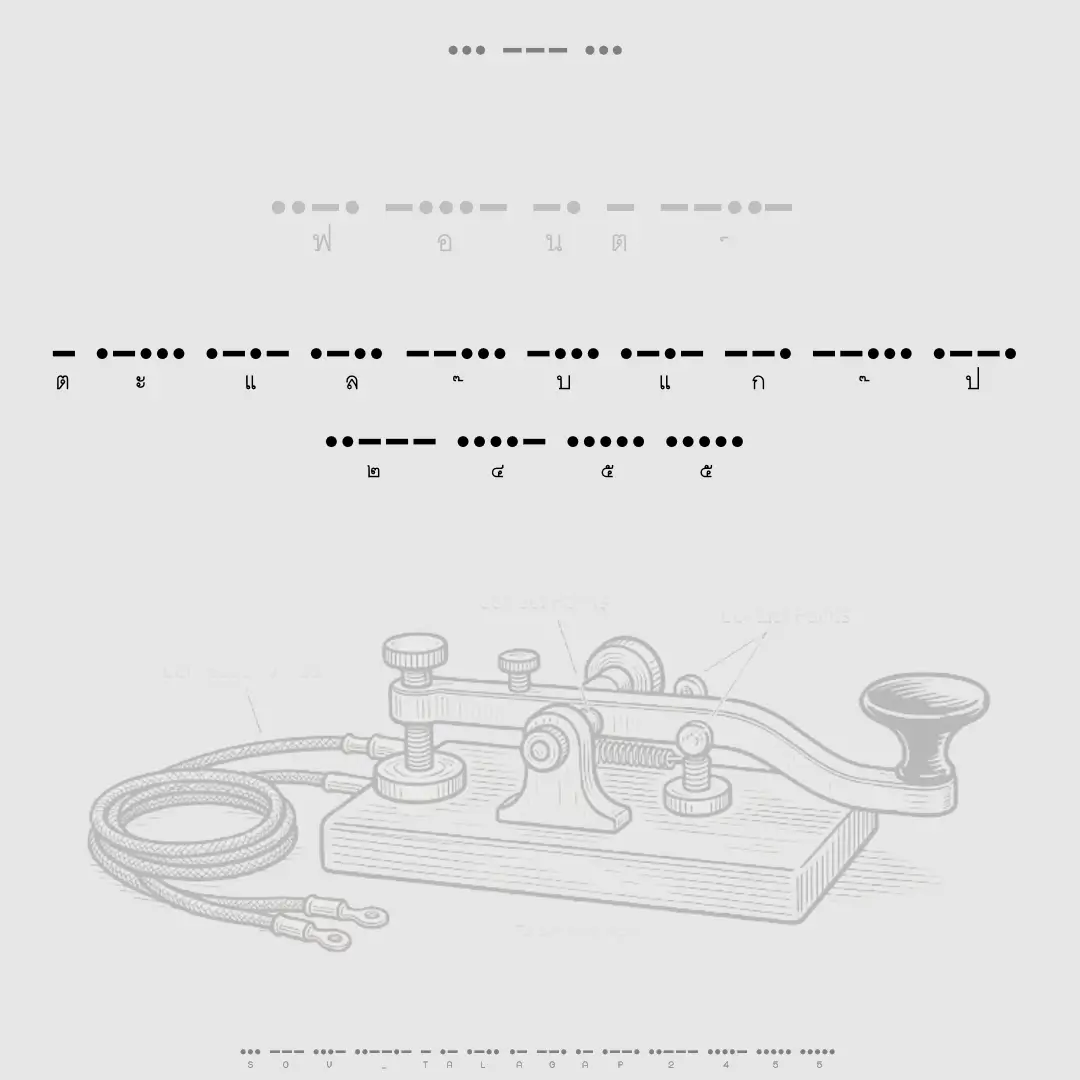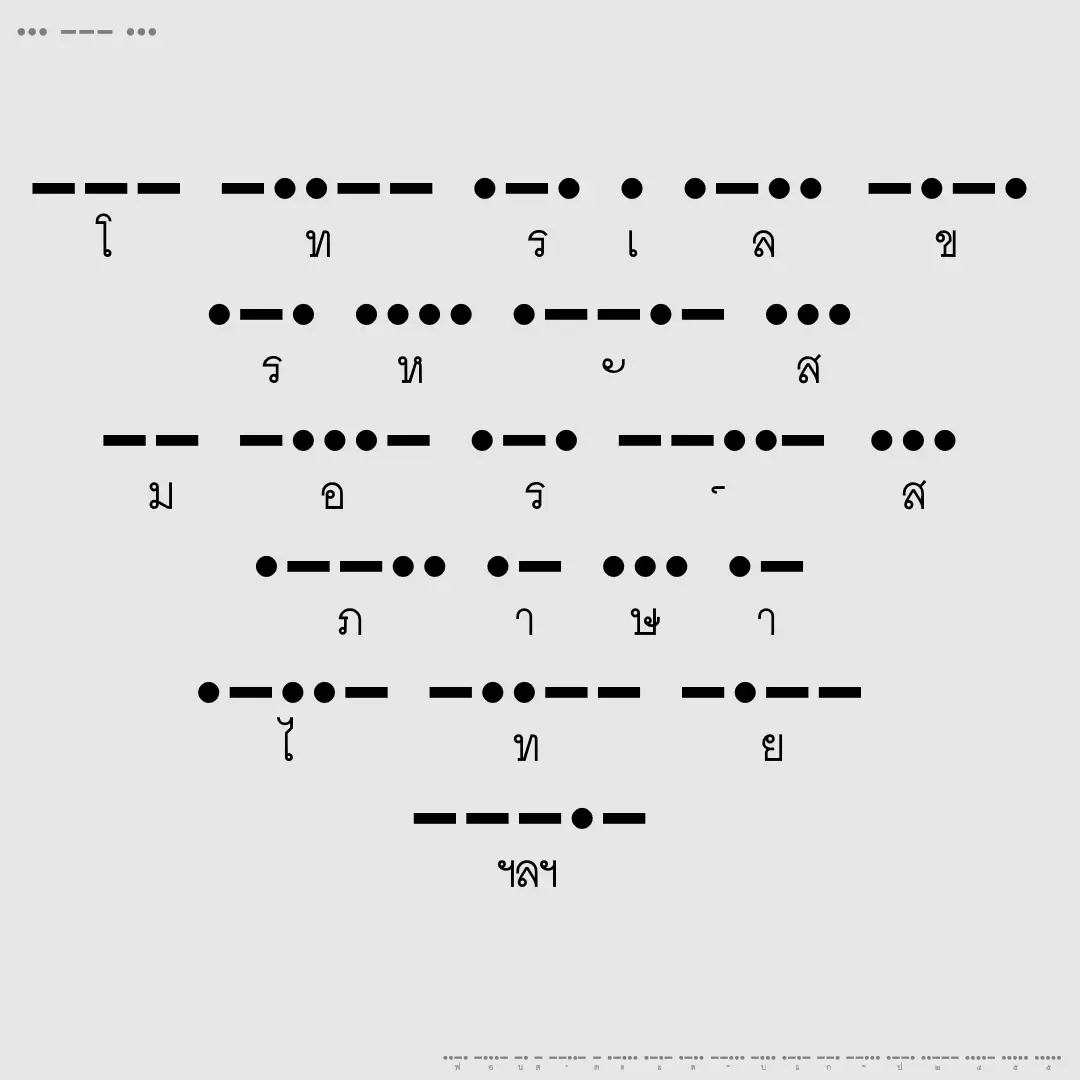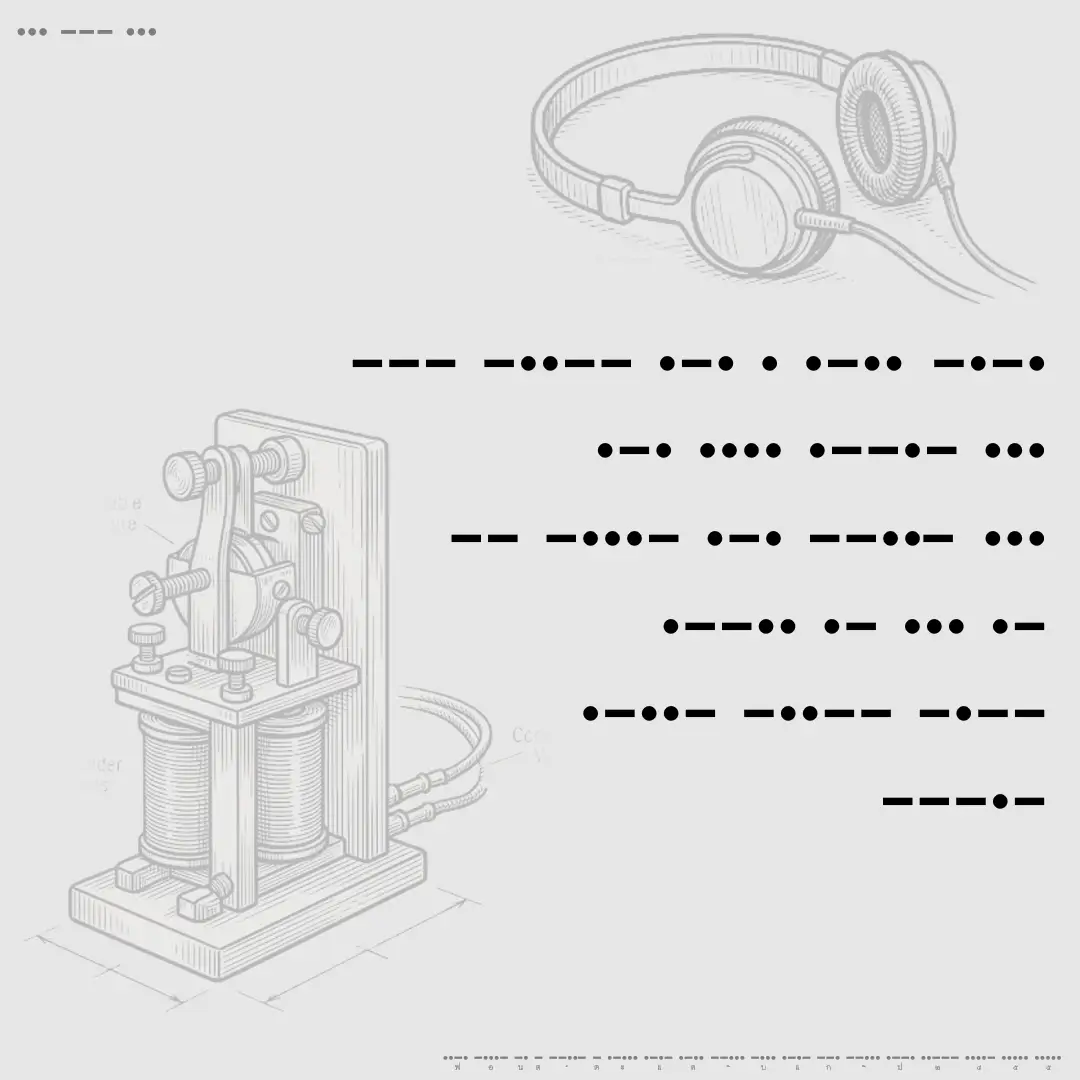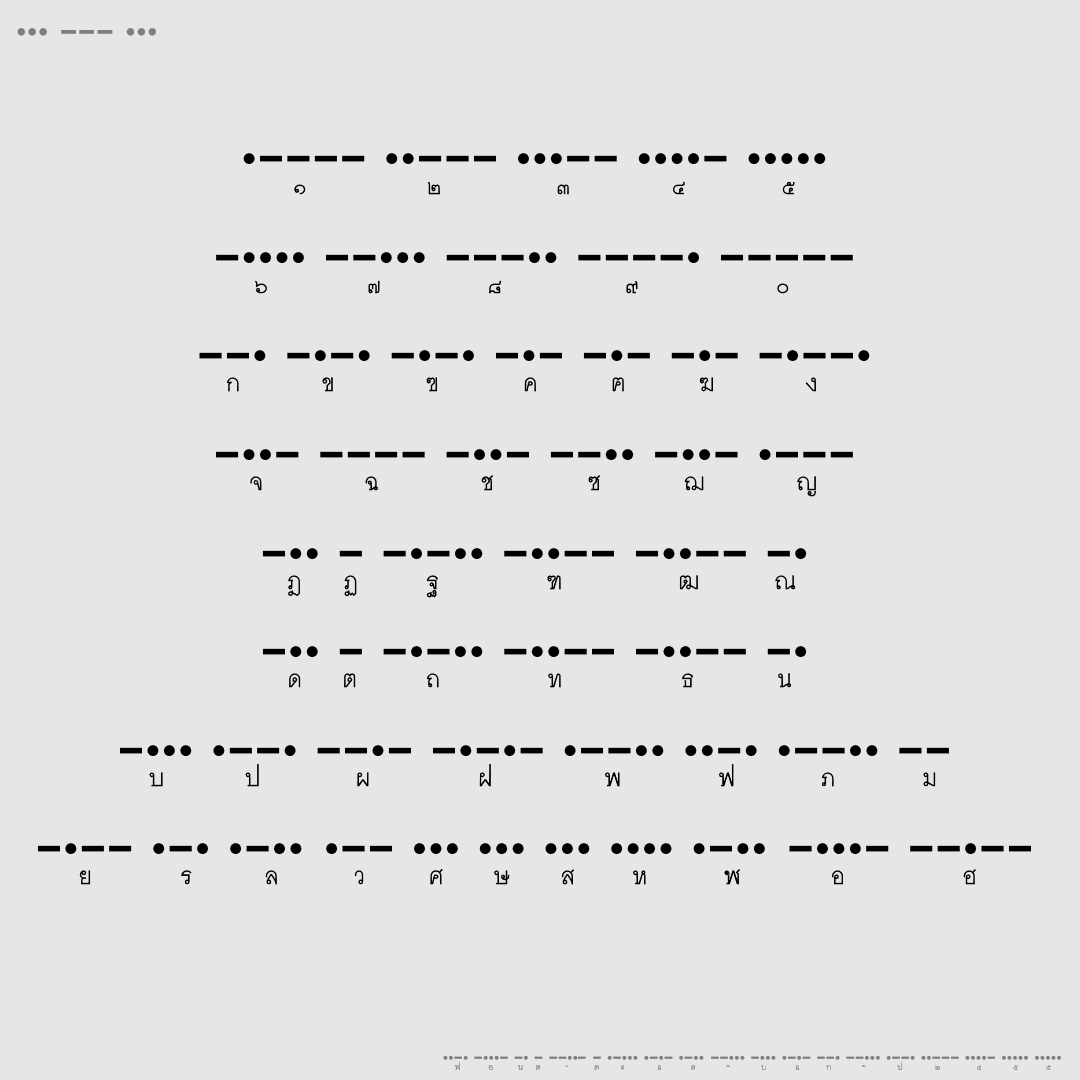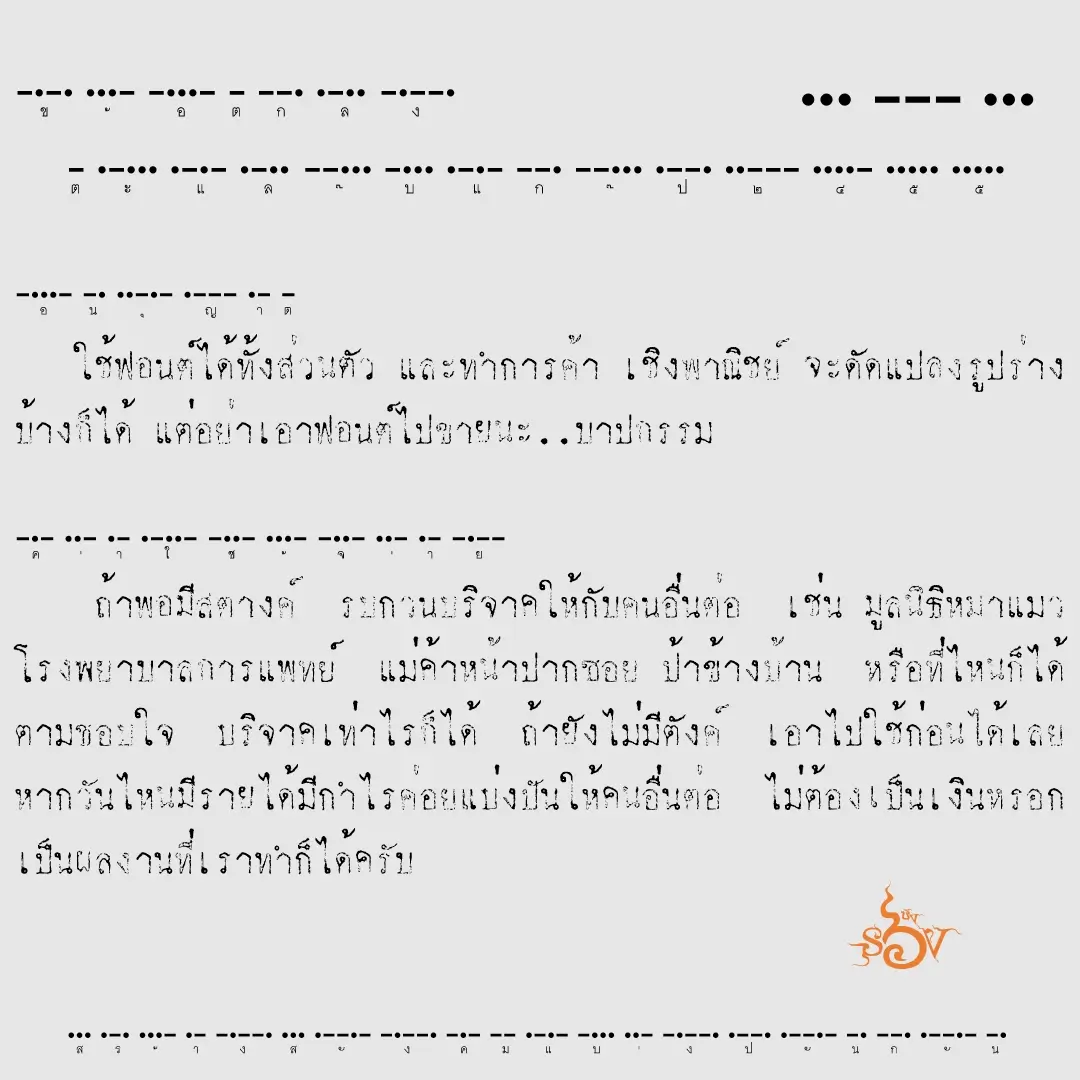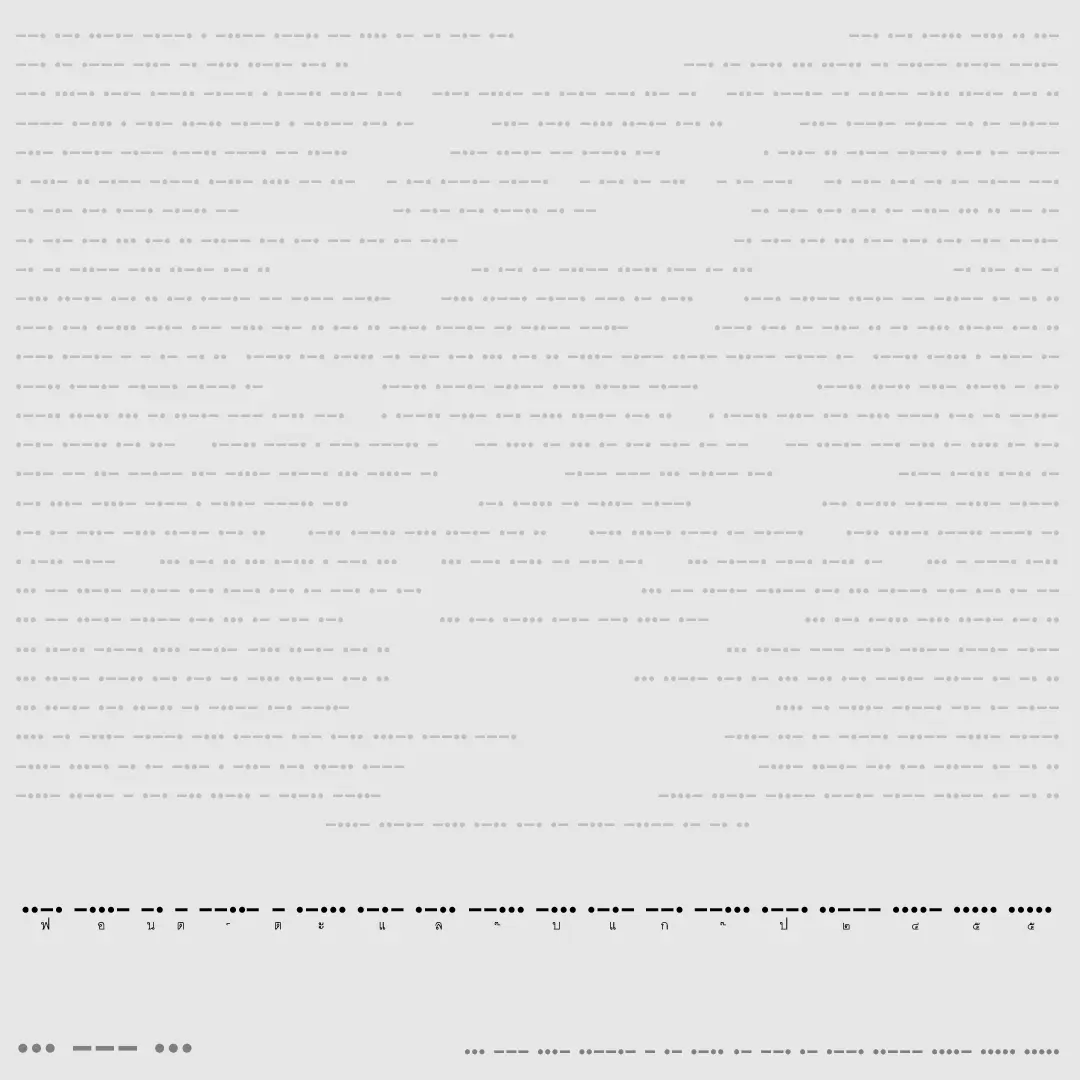
ตะแล๊บแก๊ป๒๔๕๕ (SOV_talagap2455)
ฟอนต์ตะแล๊บแก๊ป๒๔๕๕ – “จุด จุด ขีด ขีด ขีด ขีด จุด ขีด ขีด ขีด จุด จุด ขีด” ตะแล๊บแก๊ป… ฟอนต์ที่อ่านไม่ออก แต่ก็อ่านออกอยู่นะ รหัสมอร์สภาษาไทย (คล่องแคล่วแล้วให้กด bold)
เบื้องหลังการออกแบบ : ตะแล๊บแก๊ป๒๔๕๕